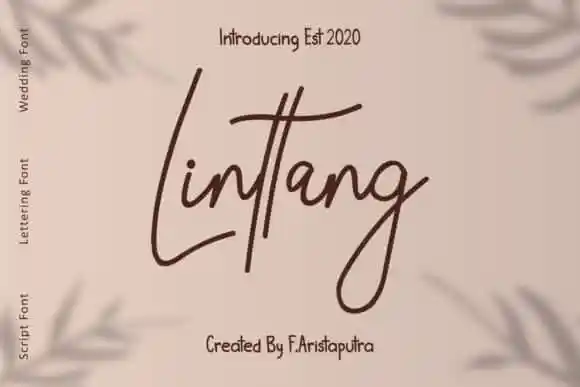
A Linttang Handwritten Font é uma escolha perfeita para aqueles que buscam um estilo elegante e contemporâneo para seus projetos digitais. Desenvolvida por Faristaputra, essa tipografia escrita à mão apresenta linhas suaves e belas formas gíli, além de sua alternativa surpreendente. O principal destaque é a influência clássica da caligrafia ao mesmo tempo que exibe uma modernidade e frescura única. Esta fonte elegante mantém o charme tradicional enquanto se destaca com linhas fluidas e formas detalhadas, tornando-a perfeita para criar trabalhos de alto nível. Descubra a Linttang Handwritten Font na 99designs, uma fonte script que certamente fará seu projeto brilhar ainda mais.